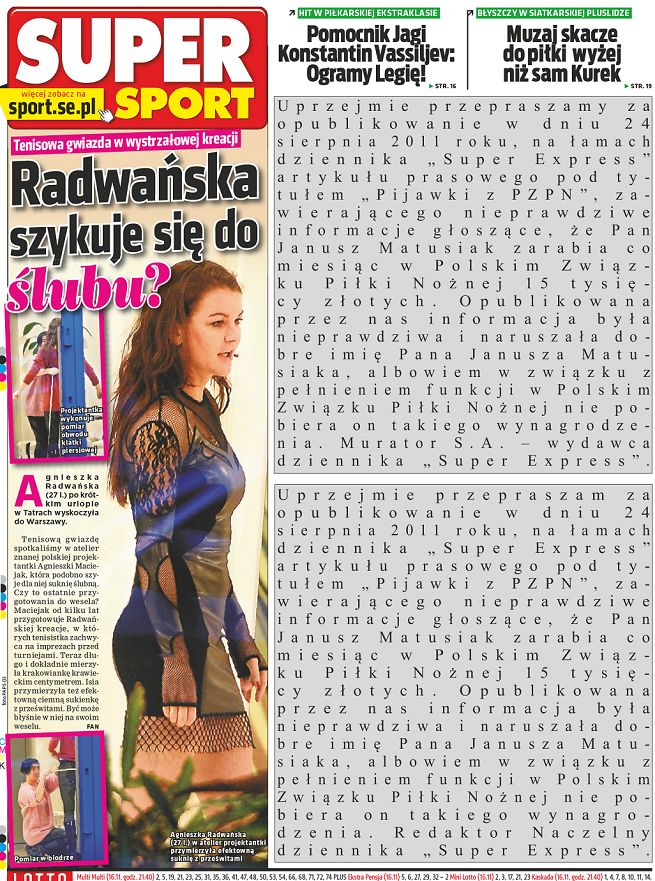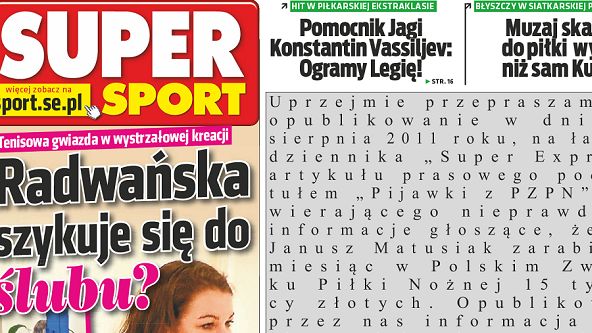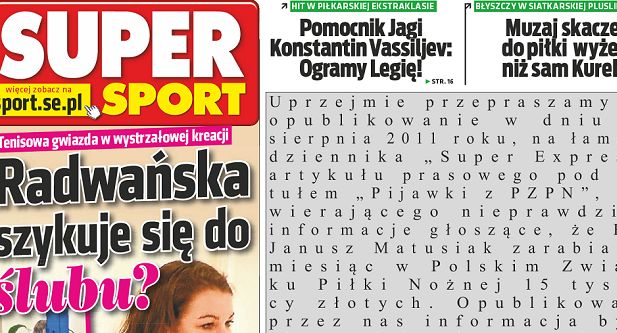
„Super Express” z przeprosinami rozstrzeloną czcionką na ostatniej stronie
W czwartkowym numerze „Super Expressu” (Murator) zamieszczono przeprosiny redaktora naczelnego i wydawcy dziennika dla Janusza Matusiaka, byłego wiceprezesa PZPN-u. Tekst zapisano rozstrzeloną, wyjustowaną czcionką.
„Super Express” z przeprosinami rozstrzeloną czcionką na ostatniej stronie
Redaktor naczelny i wydawca „Super Expressu” w czwartkowym wydaniu przeprosili Janusza Matusiaka za tekst w dzienniku z 24 sierpnia 2011 roku, w którym napisano, że Matusiak jako wiceprezes Polskiego Związku Piłki Nożnej zarabiał co najmniej 15 tys. zł miesięcznie. W przeprosinach przedstawiciele „SE” przyznają, że to nieprawdziwa informacja naruszająca dobra osobiste Matusiaka, który nie pobierał wynagrodzenia z PZPN-u.
Tekst jest zapisany na szarym tle czarną czcionką, mocno rozstrzeloną i wyjustowaną. W konsekwencji przerwy między literami w wyrazach są niewiele większe niż między wyrazami, więc cały tekst jest dużo mniej czytelny.
Publikacja przeprosin wynika z przegranego przez „Super Express” procesu z Januszem Matusiakiem.
Przypomnijmy, że pod koniec maja 2014 roku na pierwszej stronie „SE” zamieszczono dwa teksty przeprosin, a wypełniającej resztę strony zapowiedzi tekstów redakcyjnych były w tej samej stylistyce: czarny tekst na białym tle. Tamte teksty również zapisano mocno rozstrzeloną i wyjustowaną czcionką.